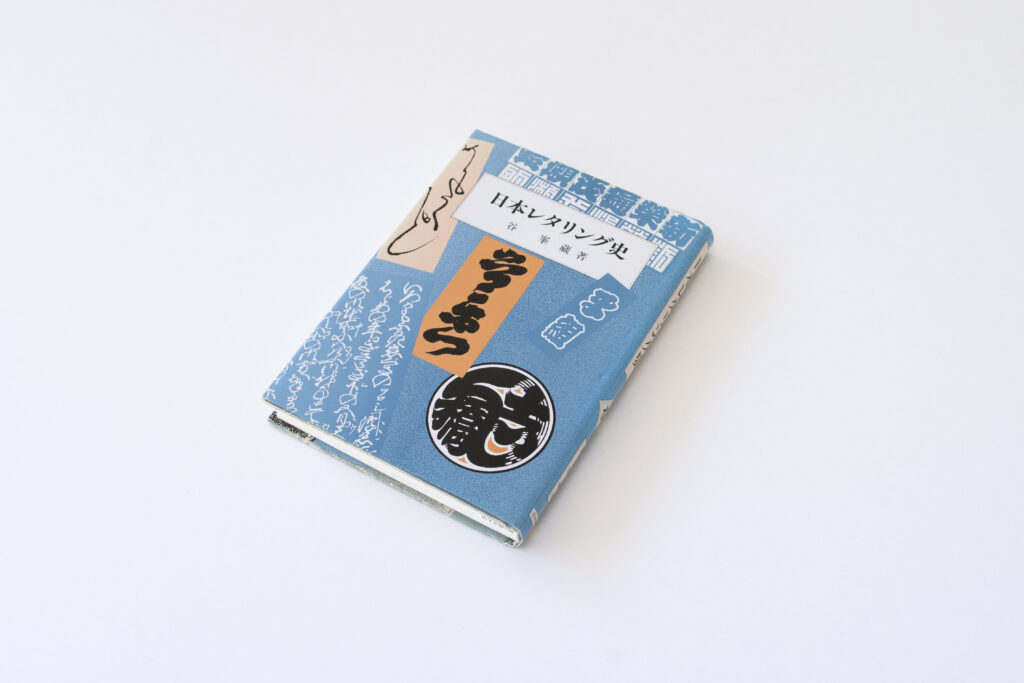
TPの書庫から『日本レタリング史』
今回は谷峯藏 著の『日本レタリング史』を紹介します。
寺社扁額の構成書体(タイポグラフィ)さまざま、和様書流の系譜、江戸期各職域のタイポグラフィ、の三章立てで日本のレタリング史について書かれた本です。
巻頭にたっぷりと掲載されている扁額の書跡が、この本を読もうと思ったきっかけでした。個人的に意外で新鮮に感じたのは、楷書や行書の代表作で知られる平安時代の能筆家が、扁額では書風を変え、装飾的で筆太な文字など変化に富んだ意匠を残していることです。
あとがきに『その書体それぞれの呼称も今日では、あいまいになり、「江戸文字」と一括呼称にひっくるめられてしまっている。』とある江戸期のタイポグラフィについて、本文ではその書体の成り立ちとともに各呼称が細かに紹介されているのも印象的でした。
「レタリング」の他に内容から浮かんだ言葉はロゴタイプ・作字・コーポレートフォントなどでした。私はそういった自分自身がリアルタイムで目にしている文字デザインと繋げたり置き換えたりして読み進めるのが楽しかったです。
続いてタイププロジェクトの代表・鈴木功から『日本レタリング史』へのコメントと関連書籍の紹介です。
歴史を目いっぱいさかのぼって日本の書き文字(おもにディスプレイ書体)を収集した本書は、レタリングという言葉のさす範囲を広くとった点において近年の嗜好にかなう内容だろう。レタリング史に書史を加えることの可否はあろうが、日本の文字とりわけ江戸文字を語るうえでレタリングの視点は欠かせない。
筆文字を対象にした『日本レタリング史』の領域をさらに広げ、彫った文字を含めてレタリングを考えたい人は『祈りの文字』と『町まちの文字』(蓜島庸二 著)がおすすめ。2020年にこの二冊が合冊となって眺められるようになったのは喜ばしい。
レタリングは、いつしかタイポグラフィ・描き文字・作字と呼ばれるようになったが、看板文字にletter(文字を書く)の現在進行形をあてた人の感覚はすばらしい。
『日本レタリング史』
著者:谷峯藏